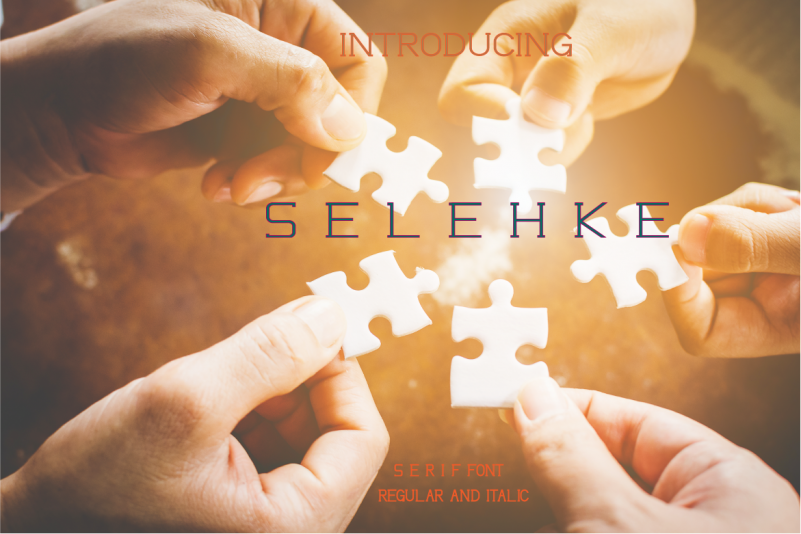
Selehkan Font
A Selehkan Font é uma mistura casual do estilo retro dos fonts san serif que incorpora elementos serifísticos para criar um equilíbrio sofisticado e natural. Desenvolvida com cuidado, a selehkan apresenta uma elegância suave e natural, ideal tanto para aplicações formais quanto para textos mais descontraídos. Esta fonte é perfeita para aqueles que buscam um equilíbrio entre a simplicidade do san serif e o charme dos serifs, resultando em letras harmoniosas e elegantes. Como designer anumb6, demonstrou uma habilidade notável ao moldar esta fonte de forma a permitir uma fusão harmônica entre as duas influências estilísticas, criando um resultado que flui naturalmente nas páginas dos seus projetos digitais ou impressos.